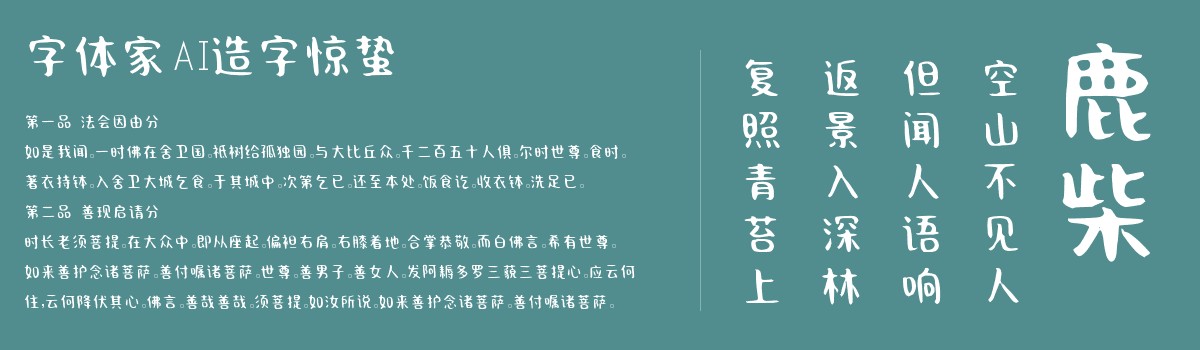
字体家AI造字惊蛰
字体家AI造字惊蛰是一款由字体家AI神笔造字生成的一款艺术字体,横画纤细挺拔,竖画沉稳粗壮,粗细对比鲜明。笔画末端有规整小衬线,似圆润钝角收束,精致不张扬。字形方正端庄,结构匀称,重心平稳。撇捺弧度流畅,转折处方中带柔,刚柔相济。整体典雅稳重,兼具传统韵味与现代简洁,线条挺括有力,平衡和谐,给人端庄又不失灵动的美感。比较适合用于艺术类装饰文字,海报、网页、广告设计,室内装饰,平面标题设计、食品包装、品牌标志等。